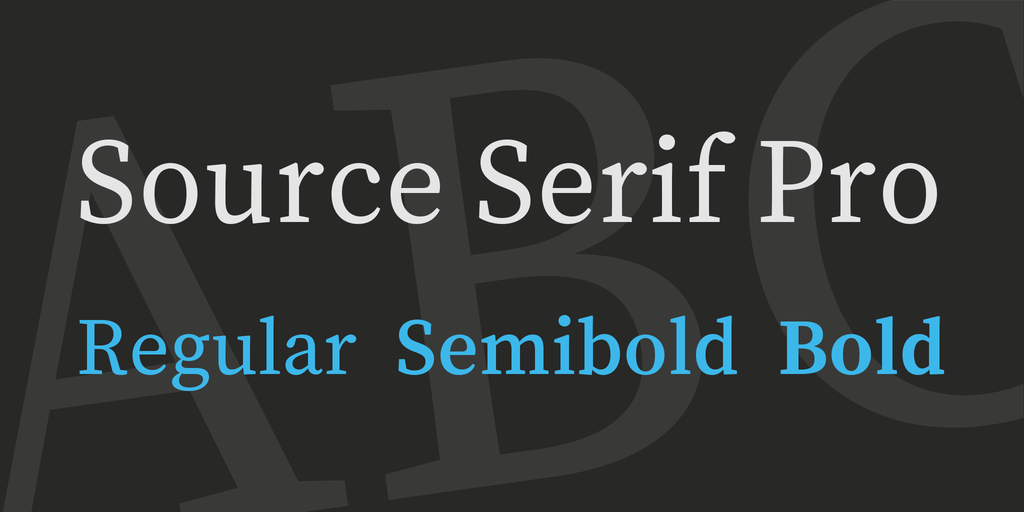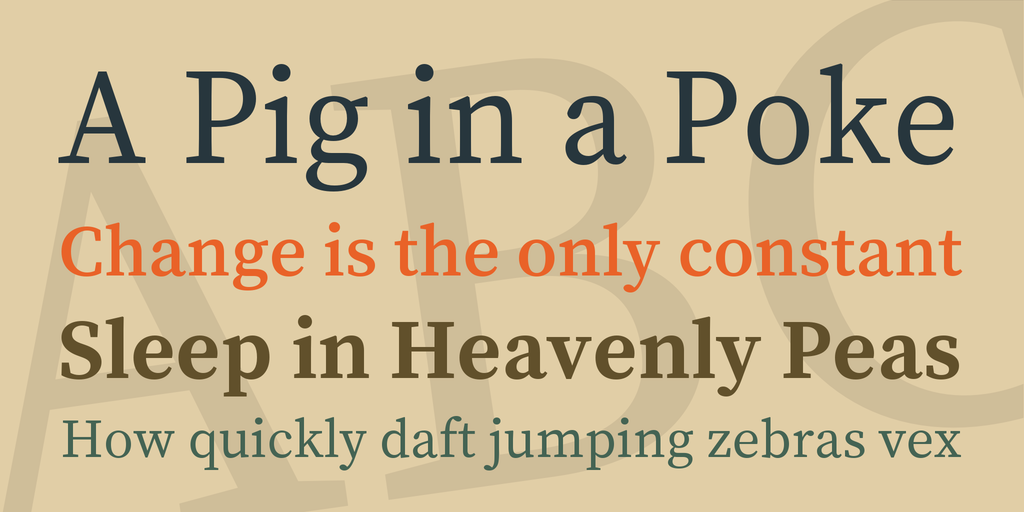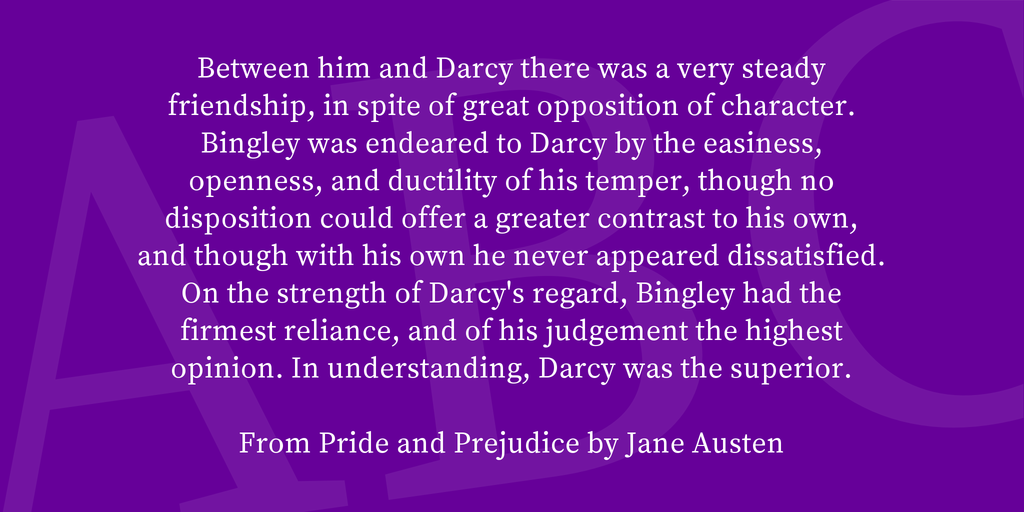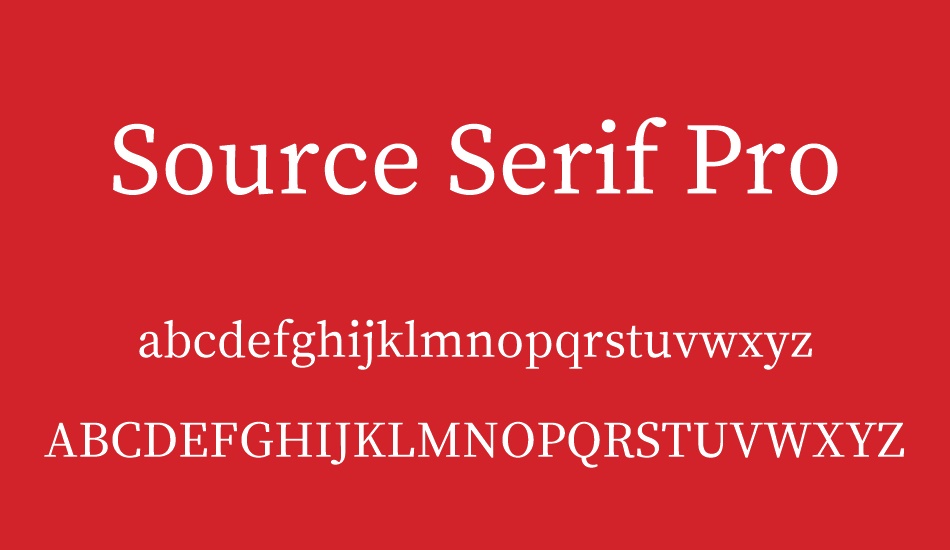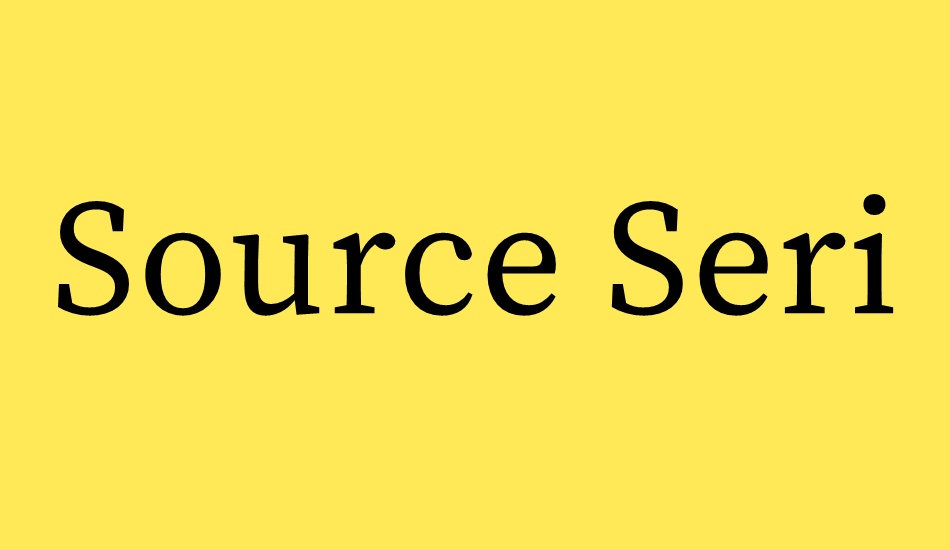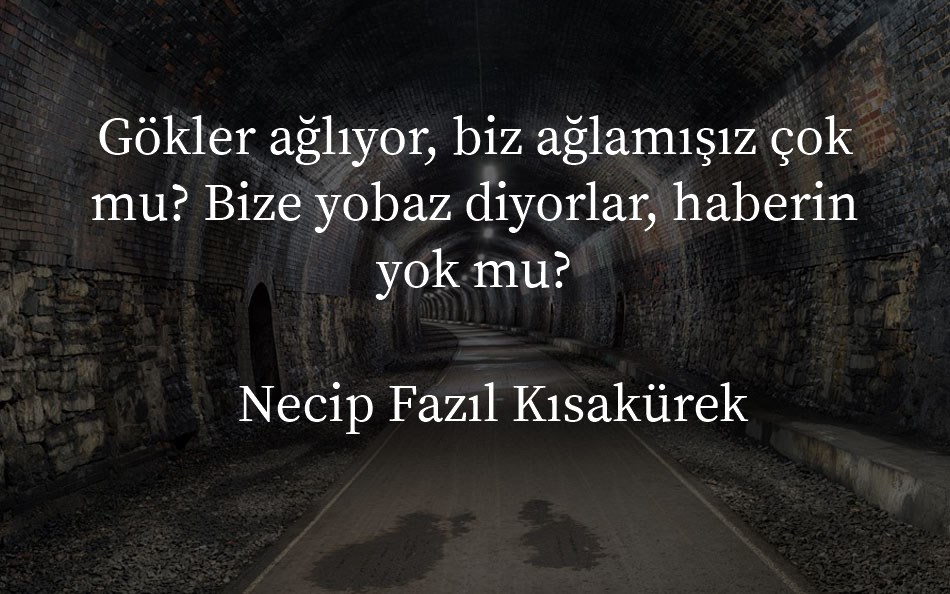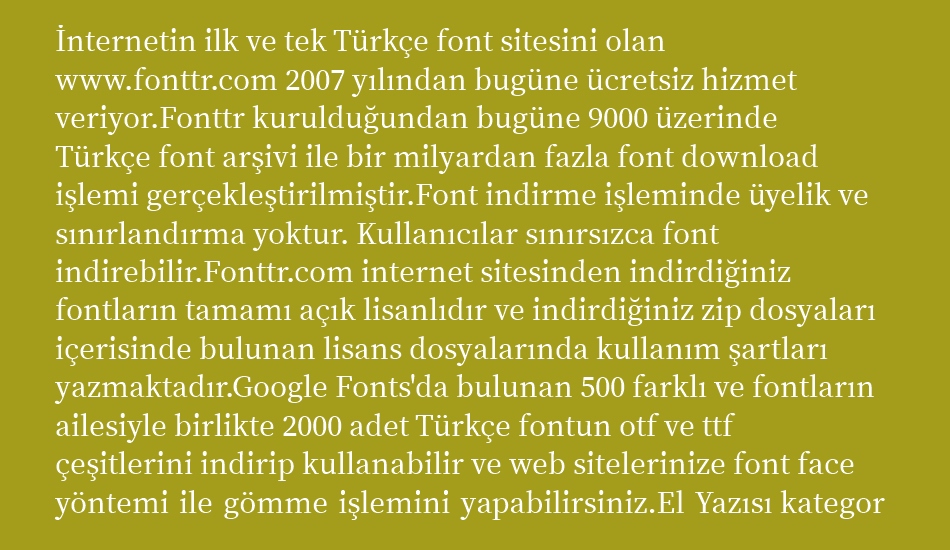
Source Serif Pro, Source Sans'ı tamamlamak üzere tasarlanmış geçiş tarzındaki bir serif yazı biçimidir. Onların yakın arkadaşlık harf oranları ve tipografik renk dikkatli bir eşleşme ile elde edilir. Serif-olmayan eşiyle uyumlu hale getirmek için tasarlanmış olan Source Serif, kısmen kendi tarihini alır, çünkü kısmen farklı tarihsel örneklerden esinlenilmiştir. Kaynak Serif gevşekçe Pierre Simon Fournier'in eserine dayanır ve Fournier'in tasarımlarına özgü birçok özellik (b'deki alt serif veya w'deki orta serif gibi) de Kaynak Serif'de bulunur. Saf bir tarihsel canlanma olmadan, Source Serif Fournier modelinden ipuçları alır ve onu modern çağa döndürür.
Source Sans ve Kaynak Serif'in de farklı kişilikleri var çünkü farklı tasarımcıların elinden geliyorlar. Kaynak Serif Frank Grießhammer tarafından tasarlanmış, Source Sans ise Paul Hunt tarafından tasarlanmıştı. Robert Slimbach, genel olarak aile uyumunun korunmasına yardımcı olan her iki tasarımdan da istifa etti. Her iki tasarım kendi başına kendinden emin hissediyor ancak aynı zamanda tasarımcılar gibi diğeriyle de birlikte çalışıyor.
Kaynak Serif Adobe'nin yüksek kaliteli açık kaynaklı yazı biçiminde olan çizgisini sürdürüyor. Dijital ortam için tasarlanan mektup şekiller basitleştirilmiş ve okunabilir niteliktedir. Tarihsel kökleri, deneyimli bir tasarımcı rehberliği ile birlikte, yazı karakterine, kağıt veya ekrandaki genişletilmiş metinler için kullanıldığında parlayacak kendine has güçlü bir karakter verir.